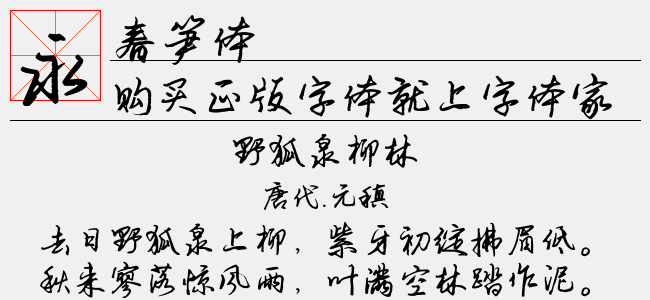
春笋体(3.26 MTTF中文字体下载)
春笋体 字体大小3.26 M,包含了6763个汉字以及附加其他英文字体和阿拉伯数字,属于点墨字库。春笋体(TTF)可以免费下载,商业用途请自行购买版权,它的特征就是手写,手书风格,行书,书法,采用安装嵌入的安装方式,支持符号拉丁文日文中文等语言
字体名称:春笋体